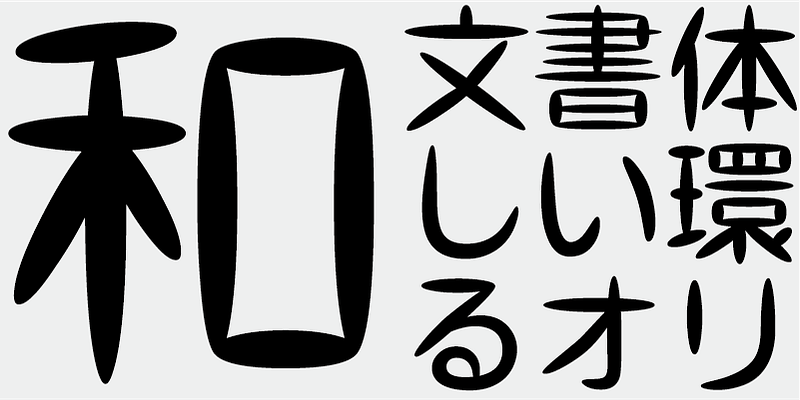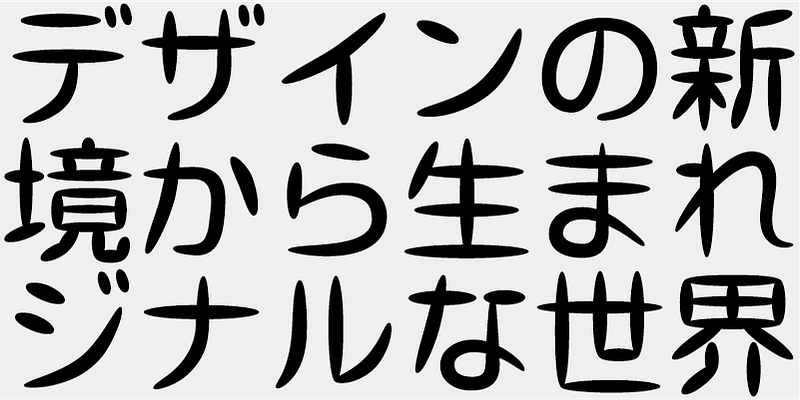
Diese Schriftart verwendet elliptische Linien, um einen sanften und freundlichen Charakter zu erzielen, mit dem eine überschwängliche Pfiffigkeit zum Ausdruck gebraucht werden kann.
Diese Schrift umfasst 1.000 wichtige Kanji-Zeichen, die aus einer von Zeitungen, Verlagen und Forschungsinstituten für Linguistik erstellten Tabelle der häufigsten Zeichen ausgewählt wurden, plus 206 Kana-Zeichen und Interpunktion.
In der heutigen japanischen Schriftproduktion gelten die 7.000 Zeichen des JIS-Standards als unabdingbar. Aber brauchen alle Schriften wirklich 7.000 Zeichen? Im Zeitalter des Fotosatzes wurden weit weniger Zeichen benötigt. FONT1000, eine Gruppe unabhängiger Schriftdesigner, ging von dieser einfachen Frage aus. Wir haben die mindestens 1.000 (ideografischen) Kanji-Zeichen ausgewählt, die für den Satz in Japanisch erforderlich sind, und aktiv Schriften und Schriftbilder dafür entworfen. Dieser 1000-Kanji-Zeichensatz wurde unter Verwendung von Zeichenhäufigkeitsdaten ausgewählt, die u. a. von Zeitungsunternehmen, Verlagen und Sprachforschungsinstituten zusammengestellt wurden, und enthält auch Kana-Silbenzeichen und Satzzeichen. FONT1000 begann 2001 mit 25 Designern und 25 Schriften. Heute haben wir 130 Schriften und sind auf fast 40 Mitglieder angewachsen, sodass wir an Schriften mit mehr Zeichen arbeiten können.